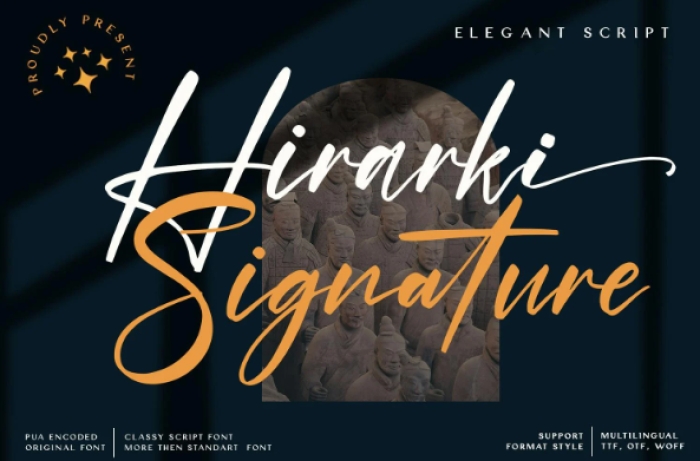
Questa raccolta di fonts veramente di alto livello sono classici esempi di caratteri che possono essere usati per simulare la scrittura a mano.
Questi 25 e oltre fonts sono stati selezionati per essere usati, vista la loro qualità, per simulare la firma e per applicare il testo del nome su documenti o grafiche